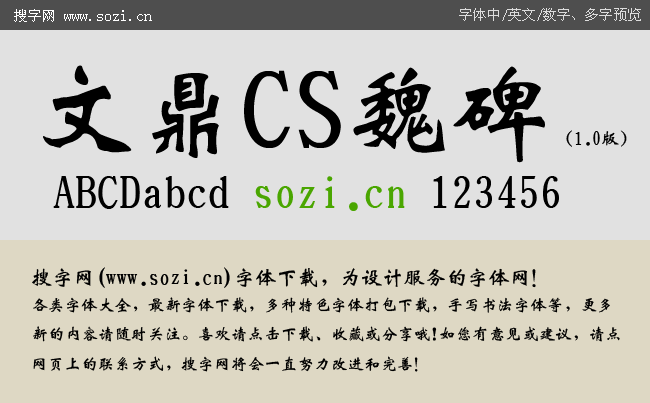
文鼎CS魏碑
搜字網(wǎng)提供一款文鼎CS魏碑中文字體下載文鼎CS魏碑是一款端正的中文字體,魏碑是一種承前啟后、繼往開來的過渡性書法體,在楷書和隸書之間,適合應(yīng)用于廣告設(shè)計(jì)、名片設(shè)計(jì)、包裝印刷、產(chǎn)品設(shè)計(jì)等應(yīng)用。